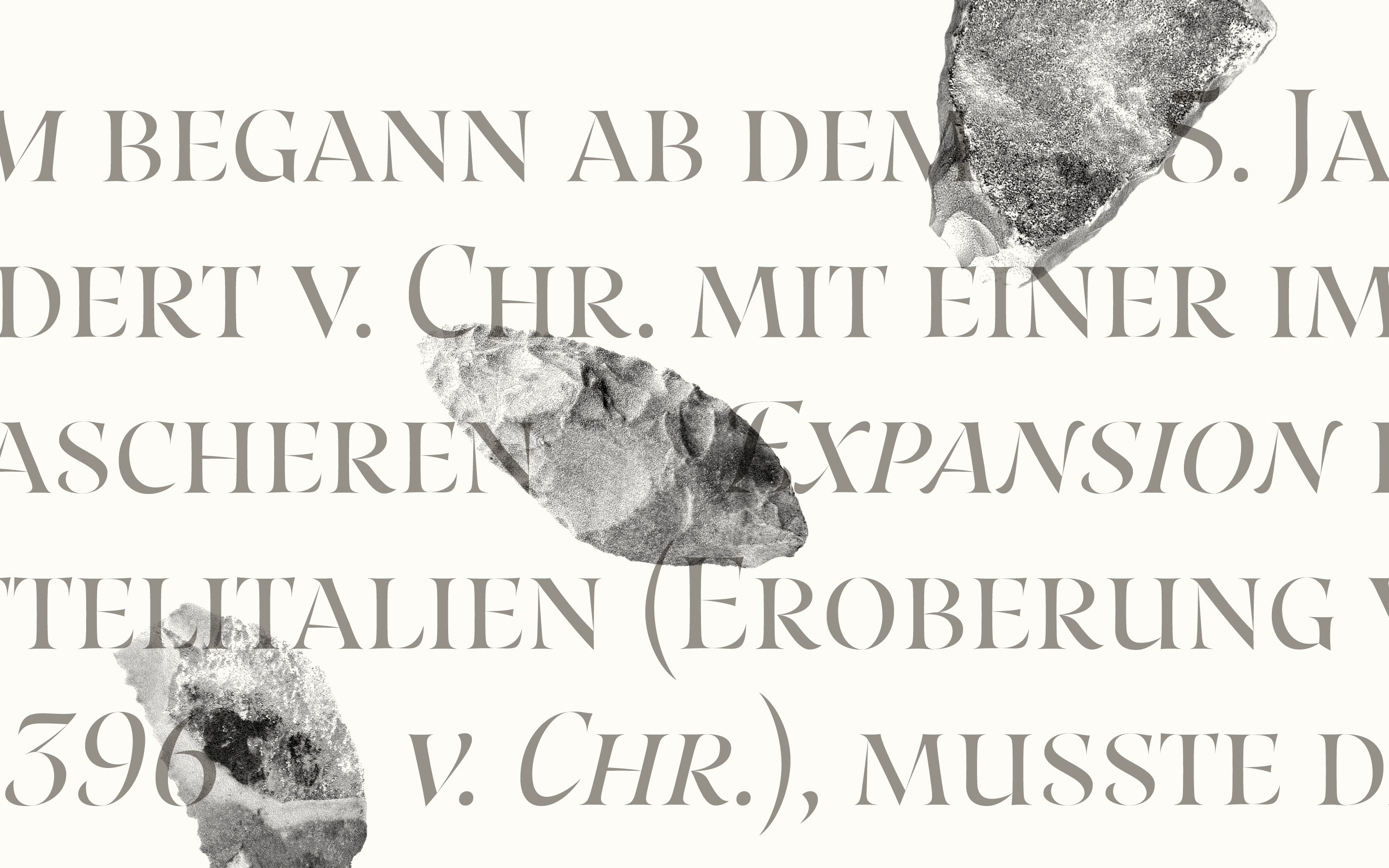
Resonay
Ein Layer-Font, der das historische Potential klassischer Schriften neu interpretiert.
Resonay ist ein dynamischer Layer-Font, der klassische Buchstabenformen in ein neues Licht rückt. Durch die Kombination der feinen Details aus der Steinmetzkunst mit dem schwungvollen Moment der Kalligrafie – einer kantigen Attitüde mit ausladenden Bézier-Kurven – ist Resonay wie gemacht für exquisite Logos und Headlines.
Reich an Schwungbuchstaben, Titelschriftvarianten und einer breiten Palette an dekorativen Ligaturen, bringt Resonay Ausdruck und Poesie in Überschriften.
Mit dem Fokus auf die klassische Typografie verfügt Resonay über angenehm breite Kapitälchen und eine Reihe von ineinander verschachtelten Versal-Ligaturen. Bei anderen Schriften mögen 200 Ligaturen ausreichen, aber Resonay geht noch weiter und liefert liebevoll gestaltete Initial- und Endschwünge für die Groß- und Kleinbuchstaben. In der Kursiven sind die Versalien von Haus aus mit Initial-Formen ausgestattet.
Resonay ist ein Layer-Font. Die Grundlage bildet Resonay Base, die mit Resonay Cover, überlagert werden kann, um mit Farbe, Deckkraft und Verläufen zu spielen. Alternativ dazu verbindet Resonay Solid beide Ebenen miteinander – für kleinere Größen und eine robuste Textur. Da alle drei Layer perfekt synchron laufen, können sie immer wieder neu kombiniert werden, um verschiedene Facetten des Textes zu betonen.
Als voll ausgestattete Display-Schrift verfügt Resonay über alle OpenType-Funktionen für anspruchsvolle Typografie. Neben vielen stilistischen Varianten der Ziffern, gibt es echte Kapitälchen und das Großbuchstaben-zu-Kapitälchen-Feature, das auch Satzzeichen mit einschließt.
Wie alle TypeMates-Schriften, verfügt Resonay über hilfreichen Symbole und eine breite Unterstützung der lateinischer Sprachen. Mit über 2.000 Glyphen in fünf Schriftstärken – Thin bis Black – und einer ausdrucksstarken Kursiven ermöglicht Resonay mit Leichtigkeit attraktive Schriftzüge.